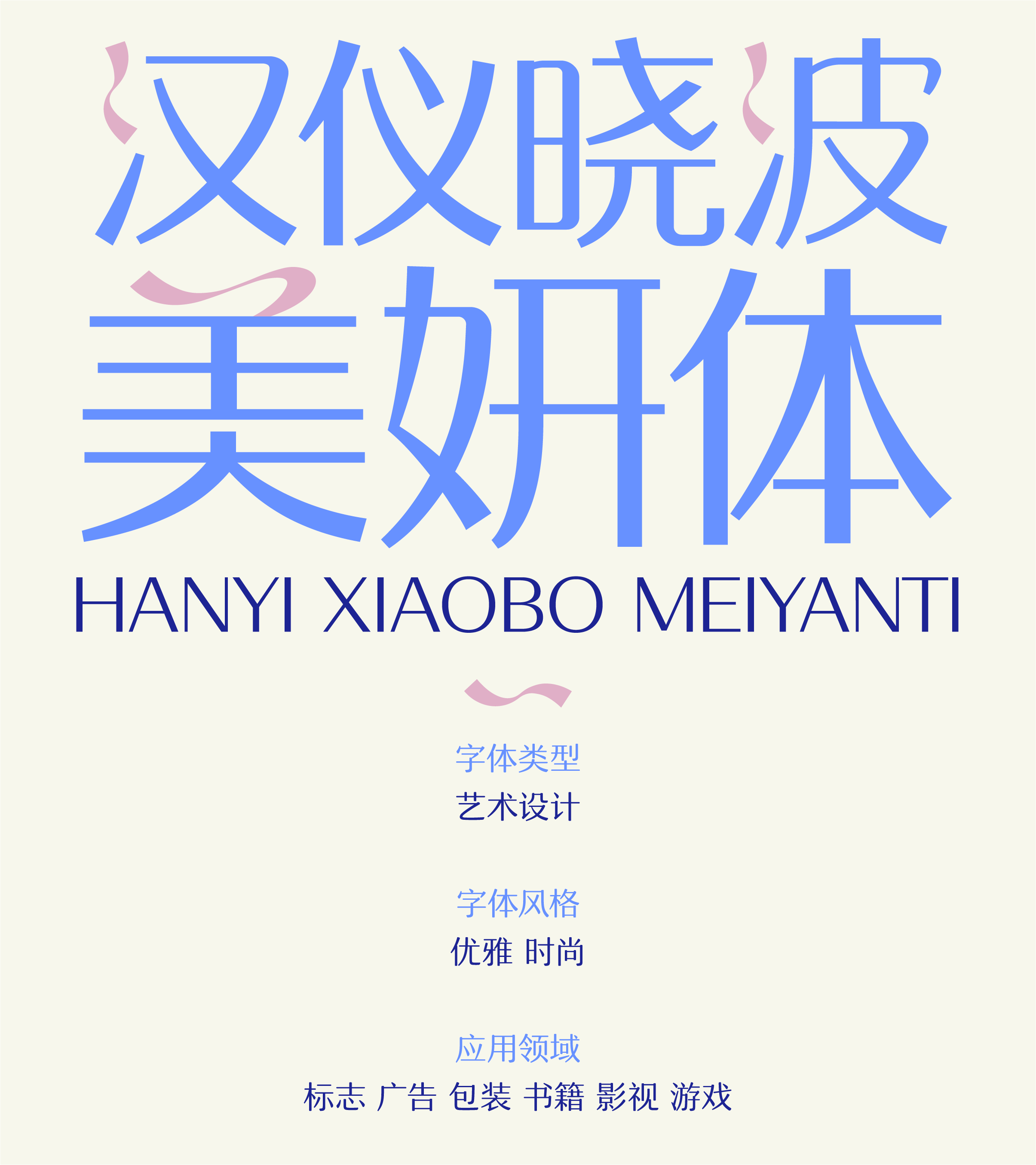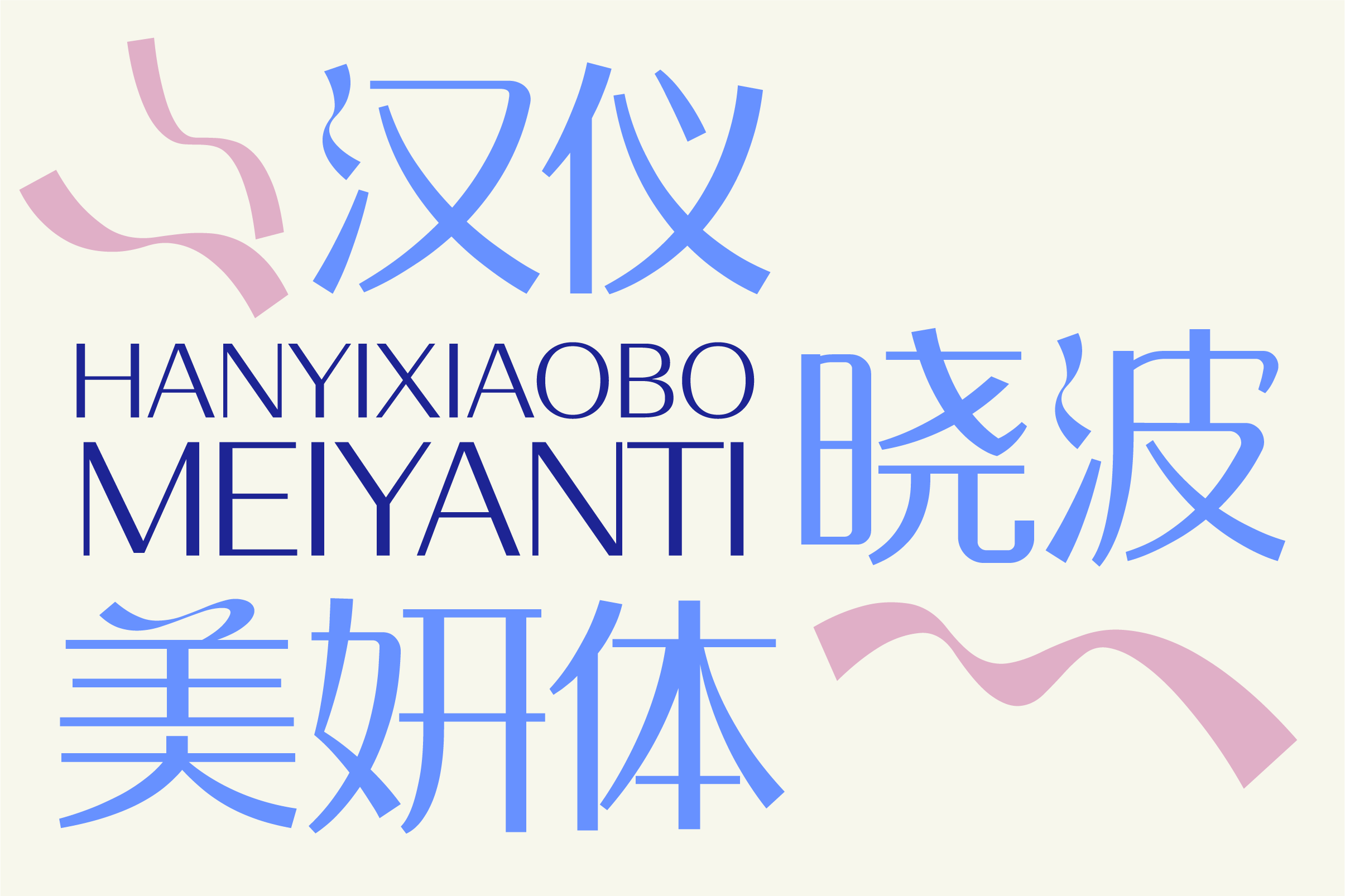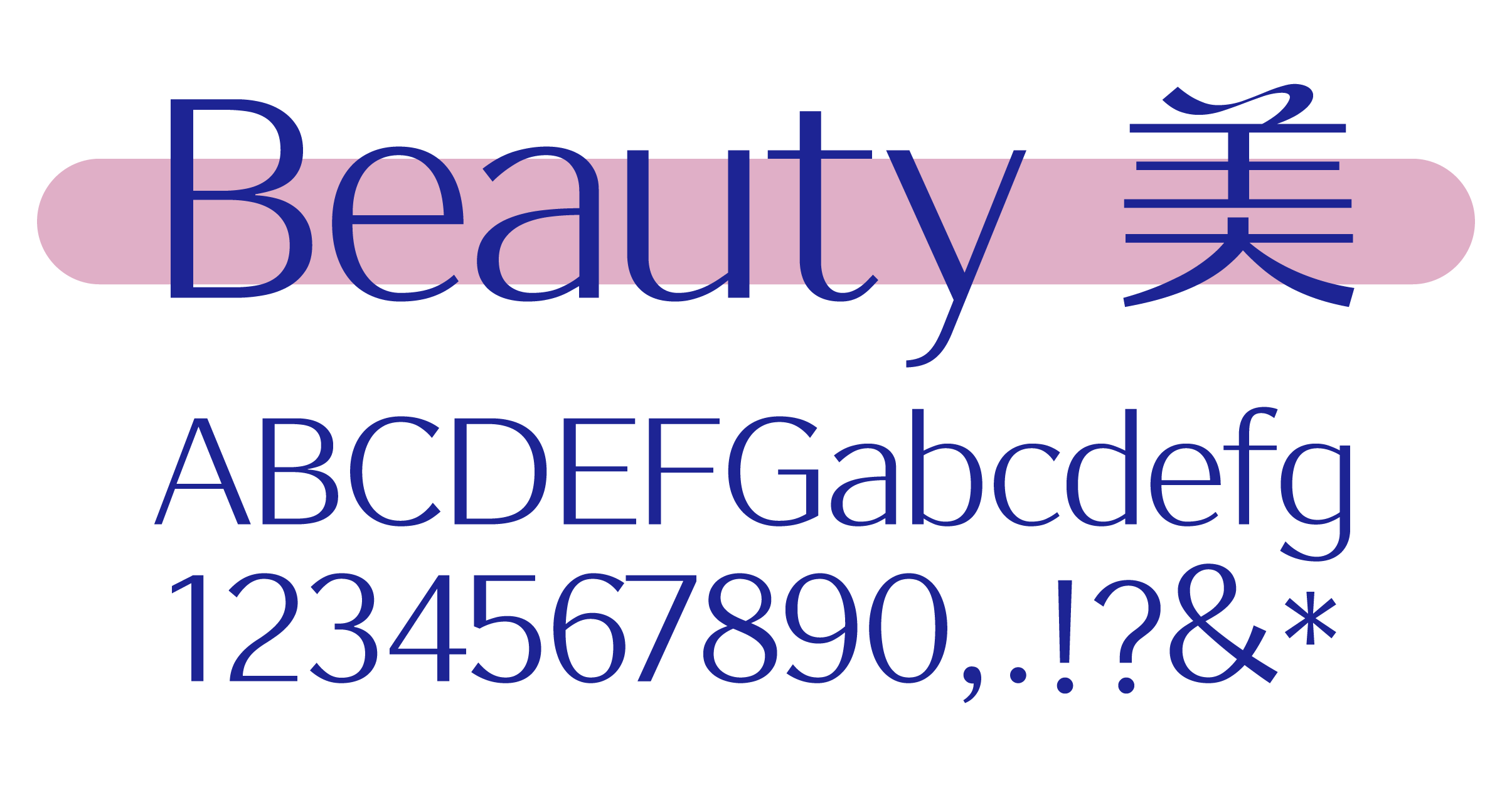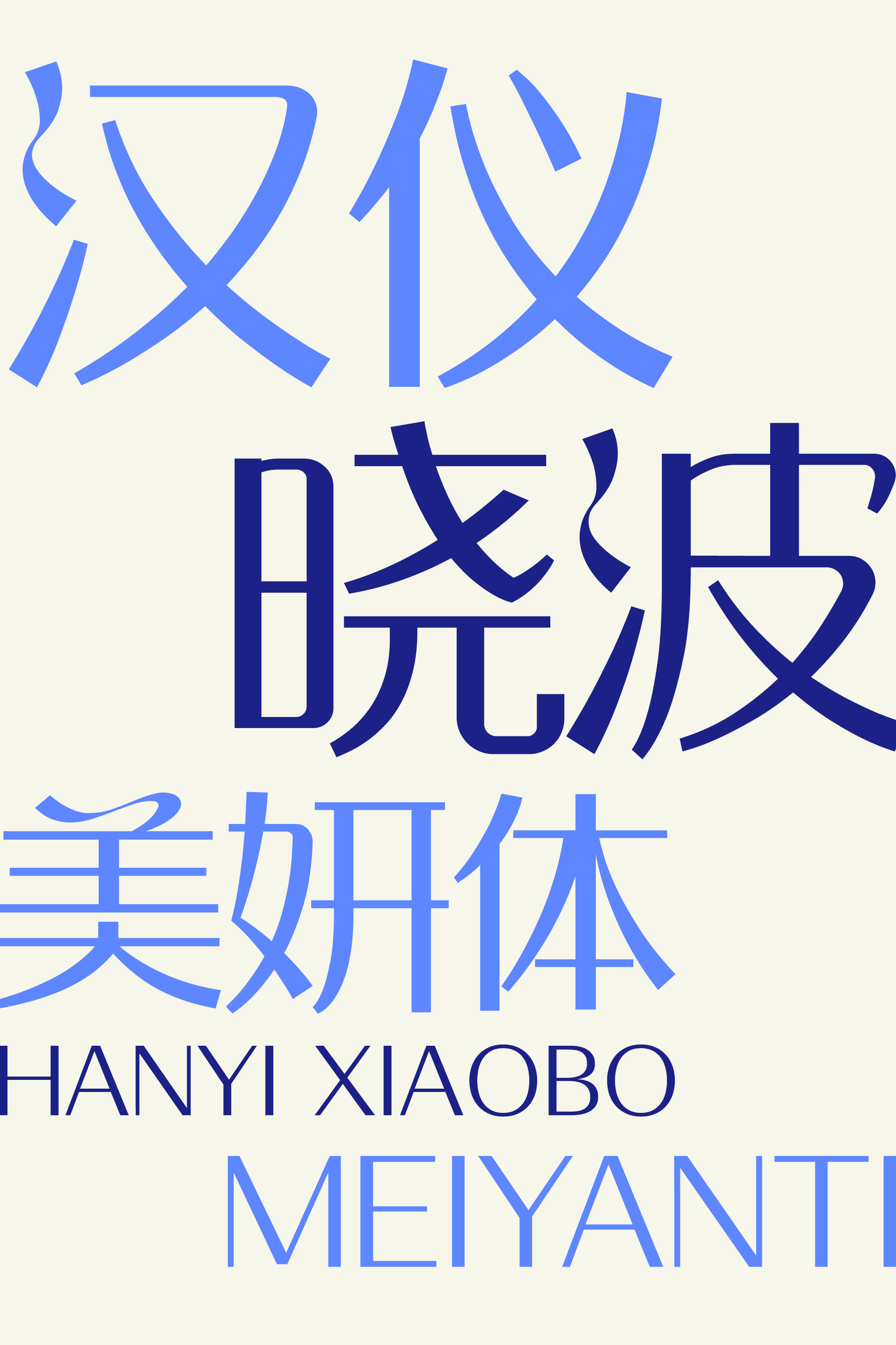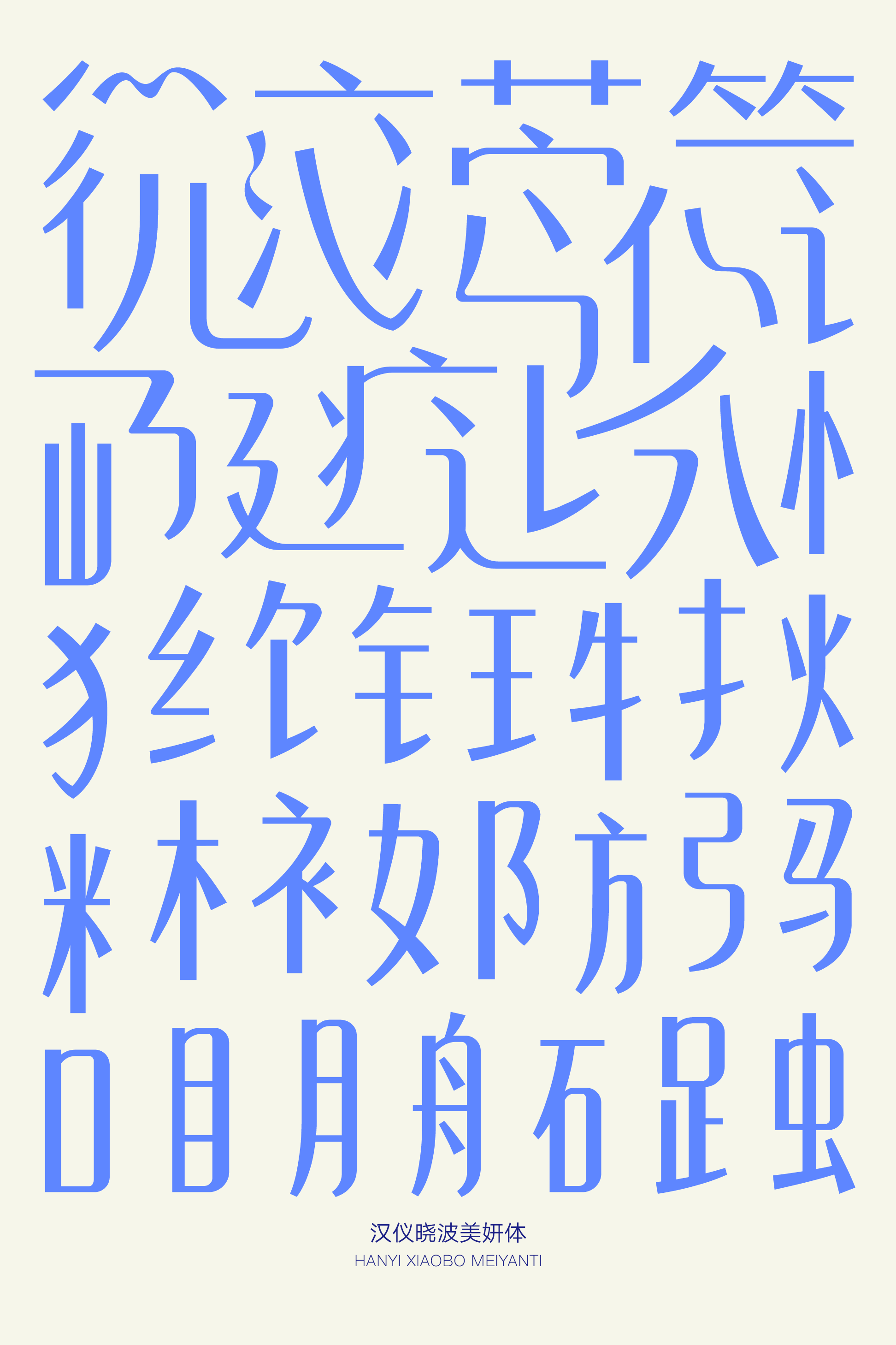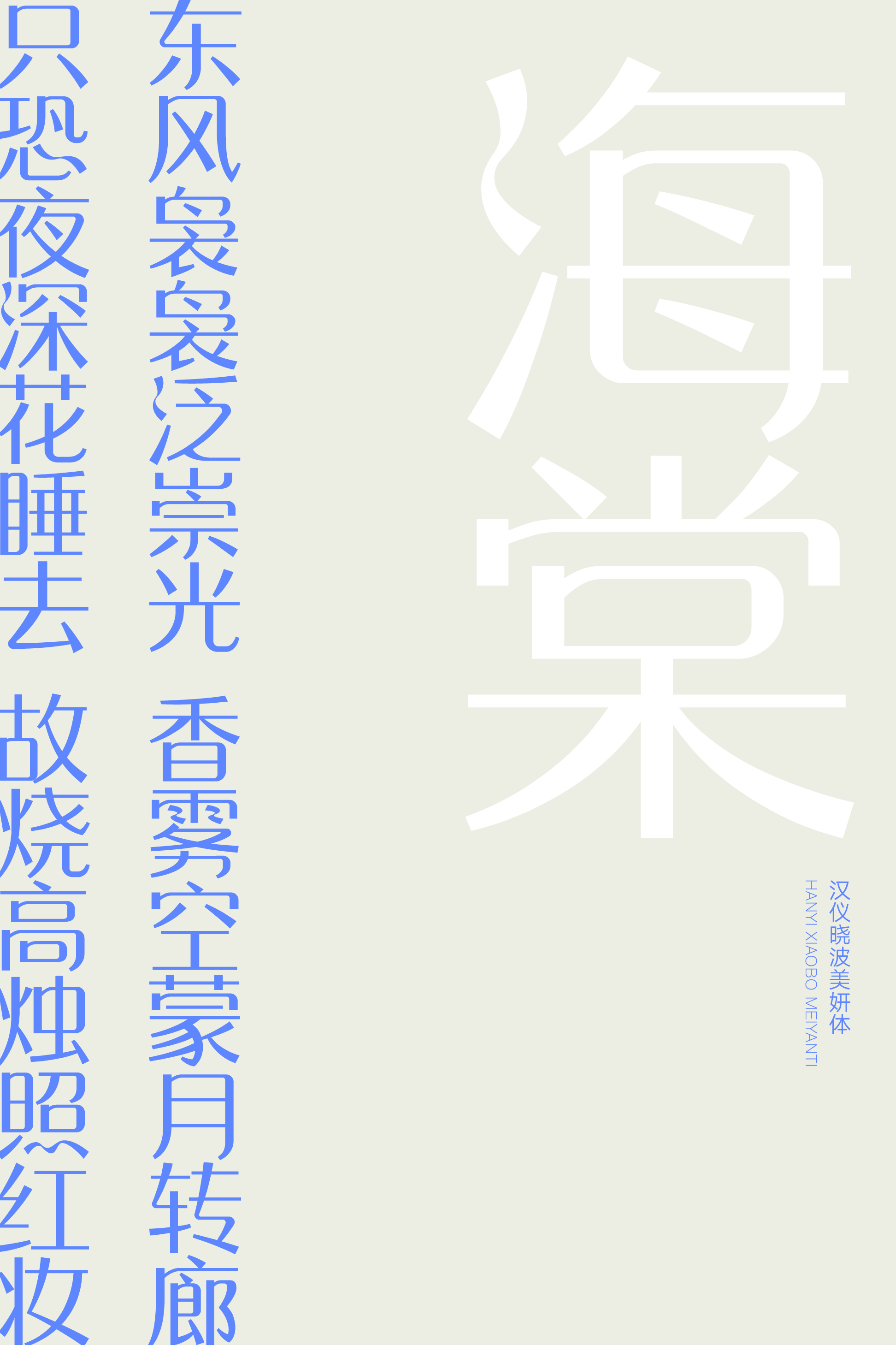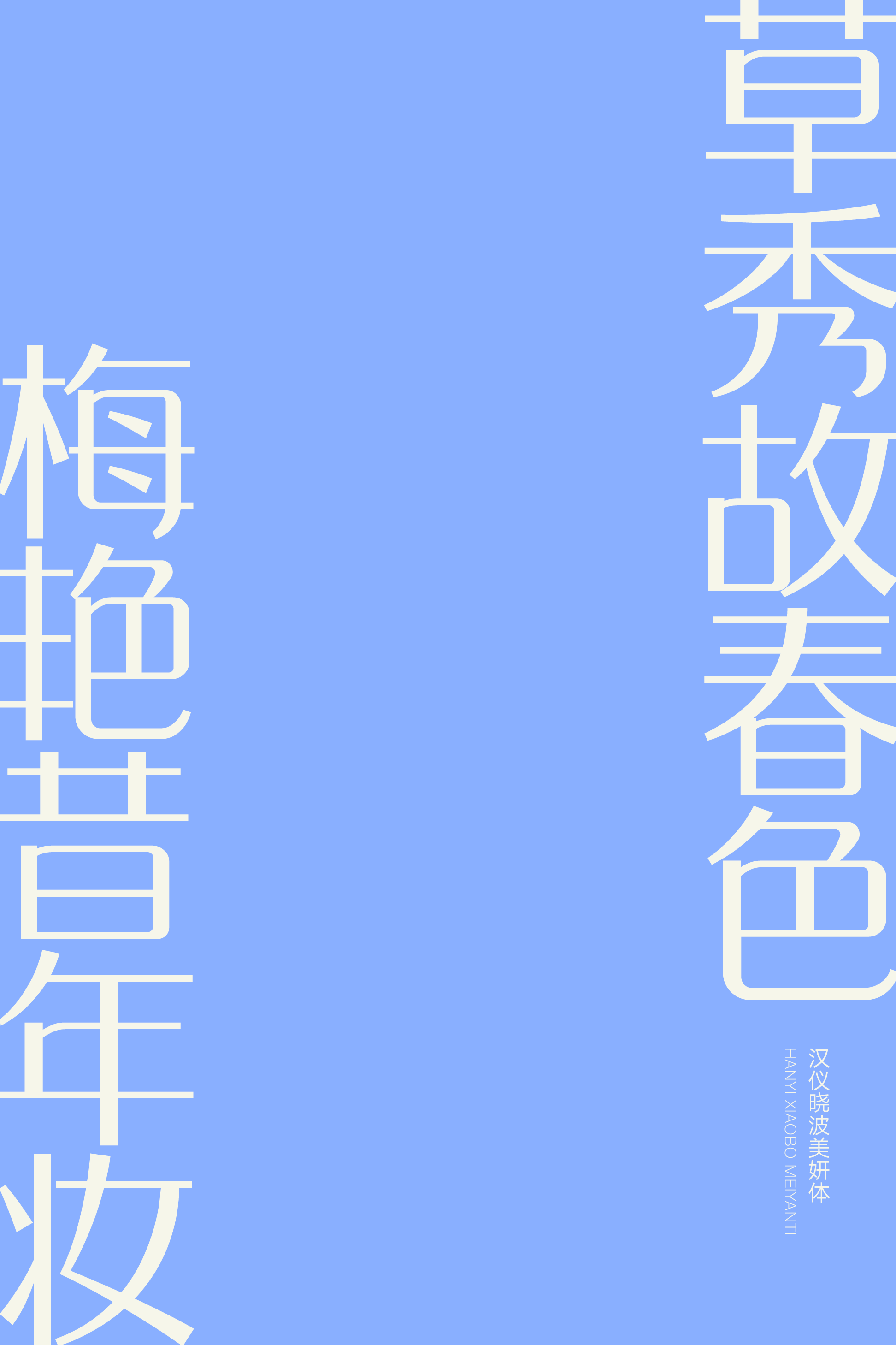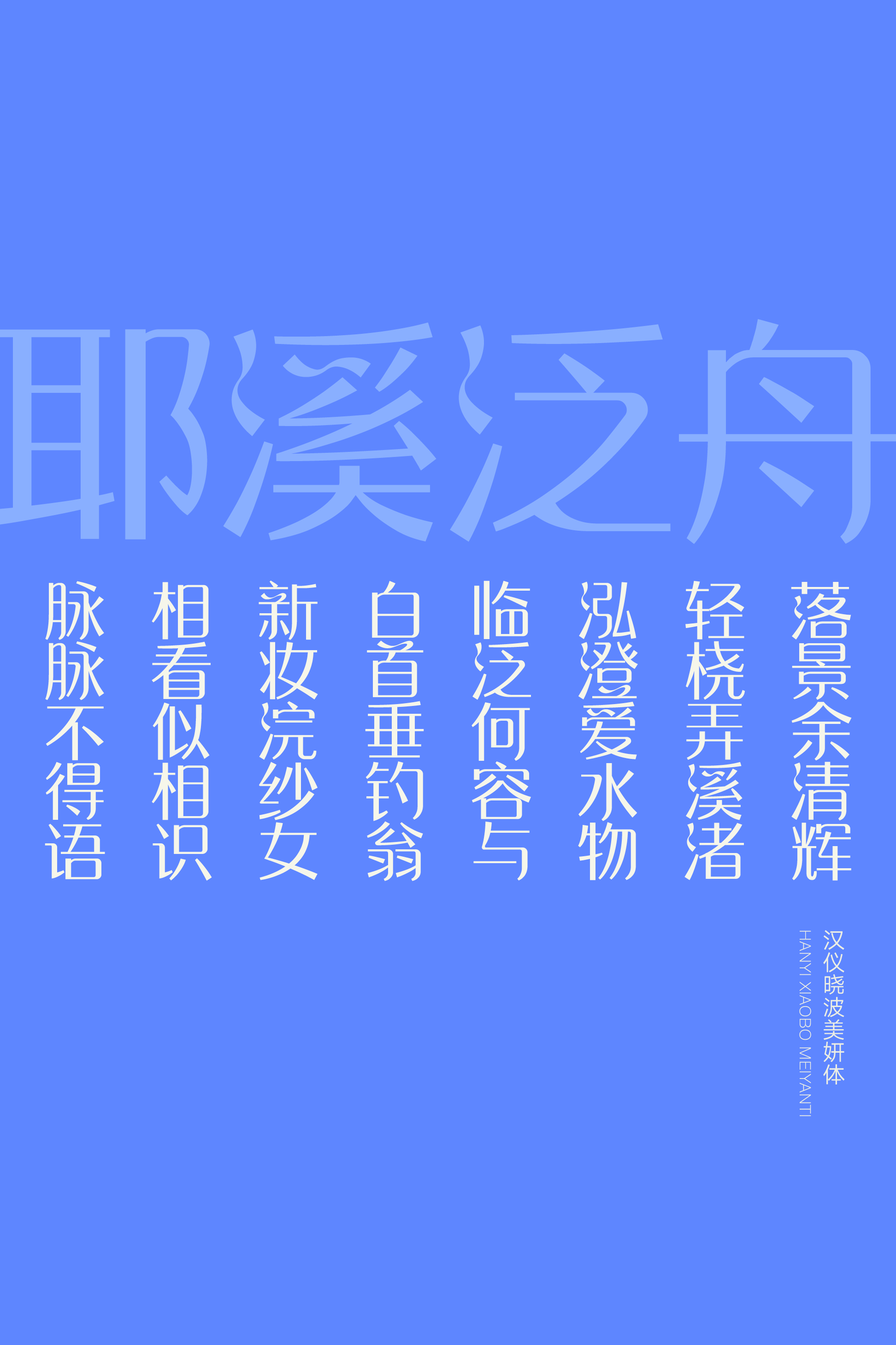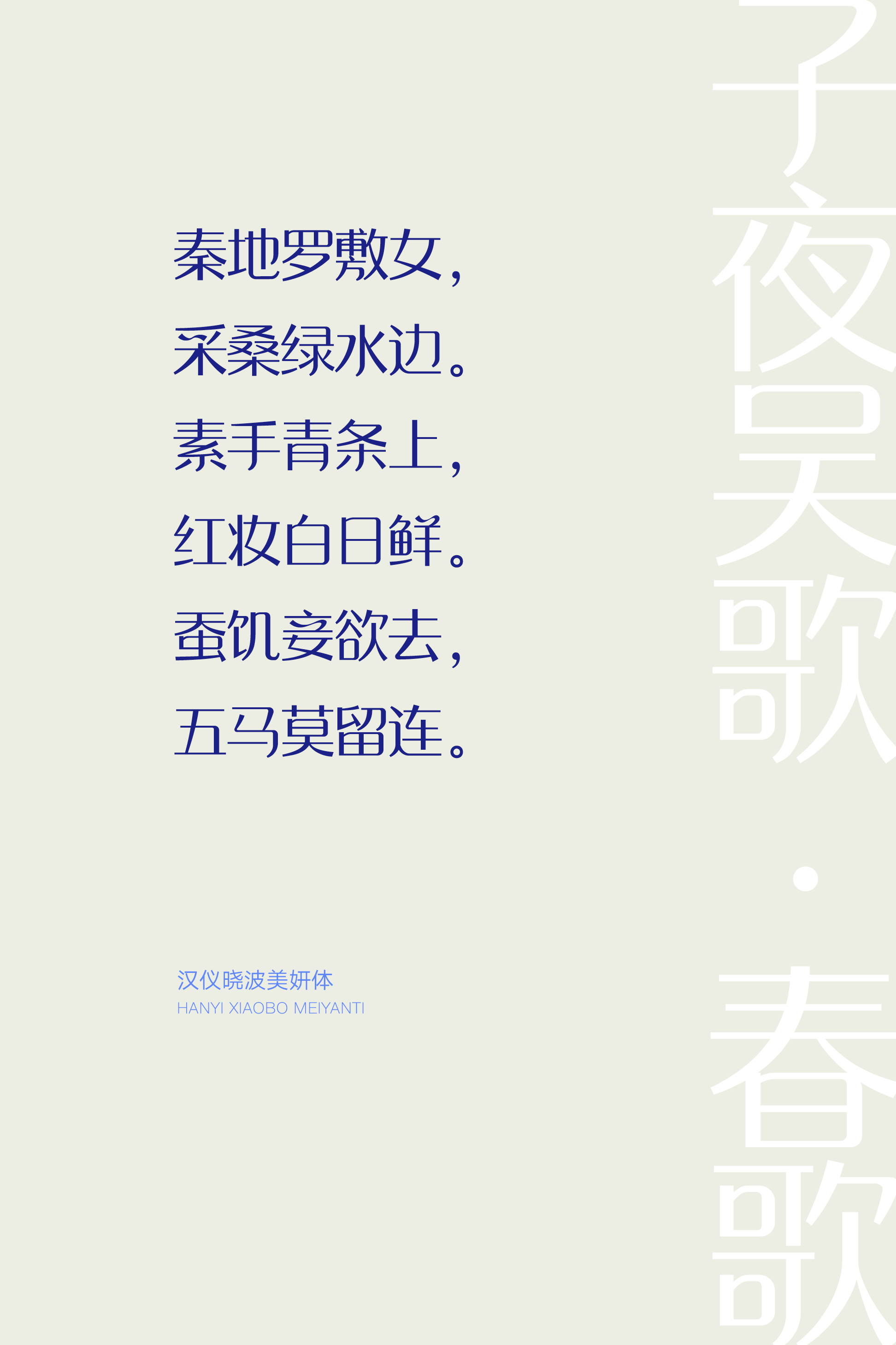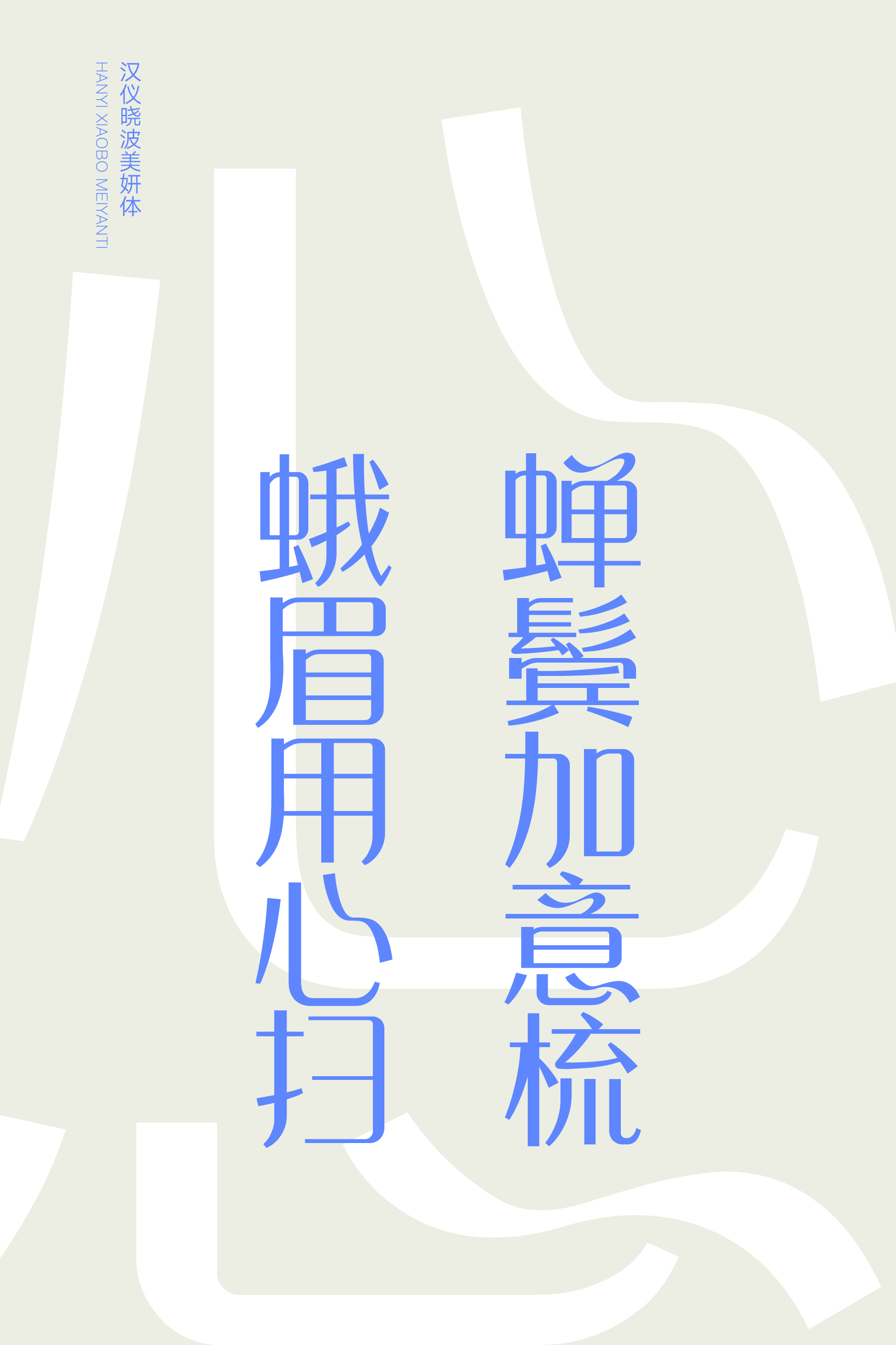
汉仪晓波美妍体
汉仪晓波美妍体,以字体为依托,寓美好圆满之意。字形饱满而通透,笔画简约大方,点画相连形成优美飘逸的缎带,点缀其中。这款字体适合作为标题或副标题字体应用于美妆时尚、节日庆典、书籍影视等使用场景,渲染浪漫温馨、优雅时尚的氛围。
字形饱满,中宫大而通透。
笔画造型简约,横竖笔画平直,弧形笔画纤美柔和。
点画相连似缎带一般优美飘逸。
西文部分选取简洁大方的无衬线风格,与中文部分匹配和谐。